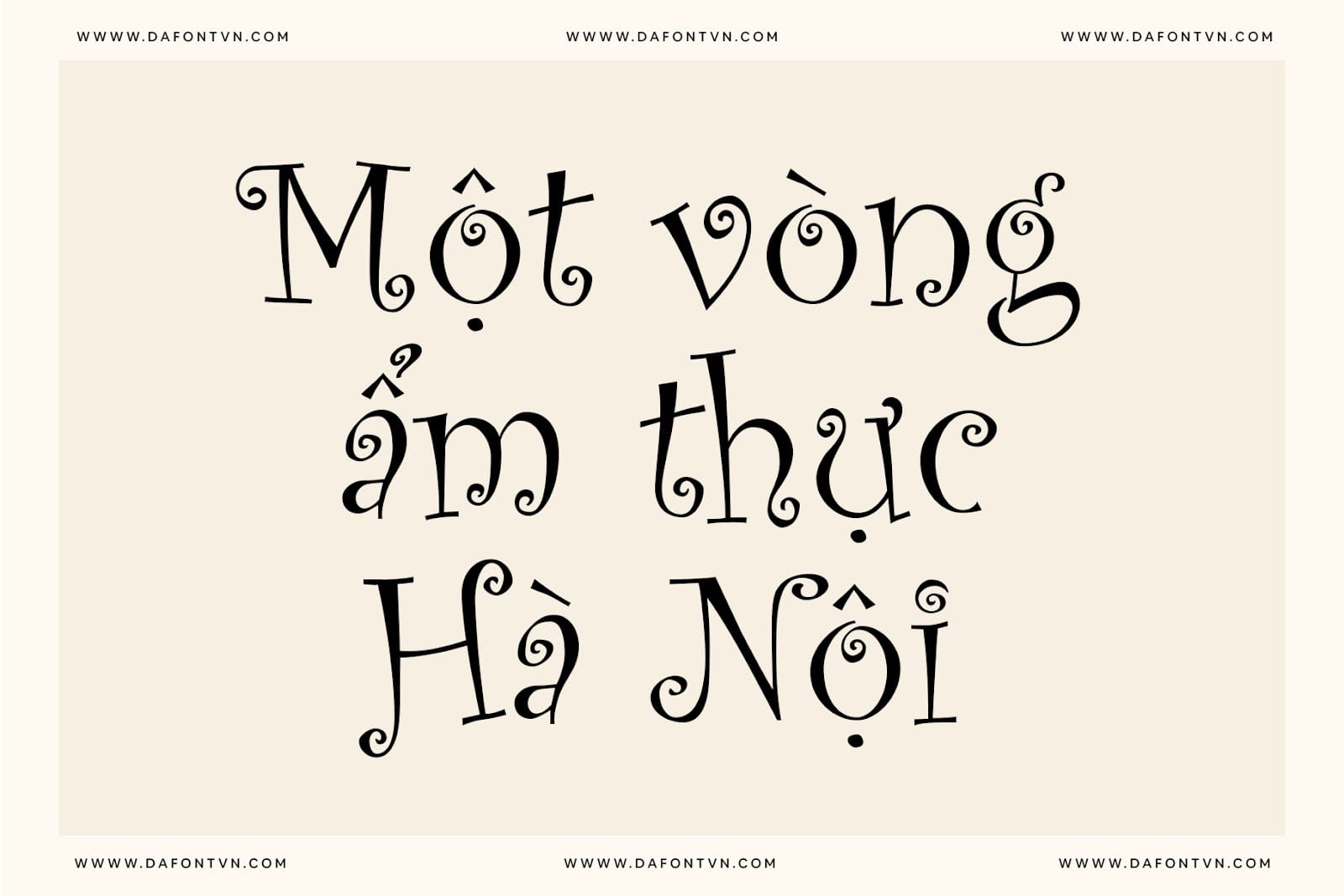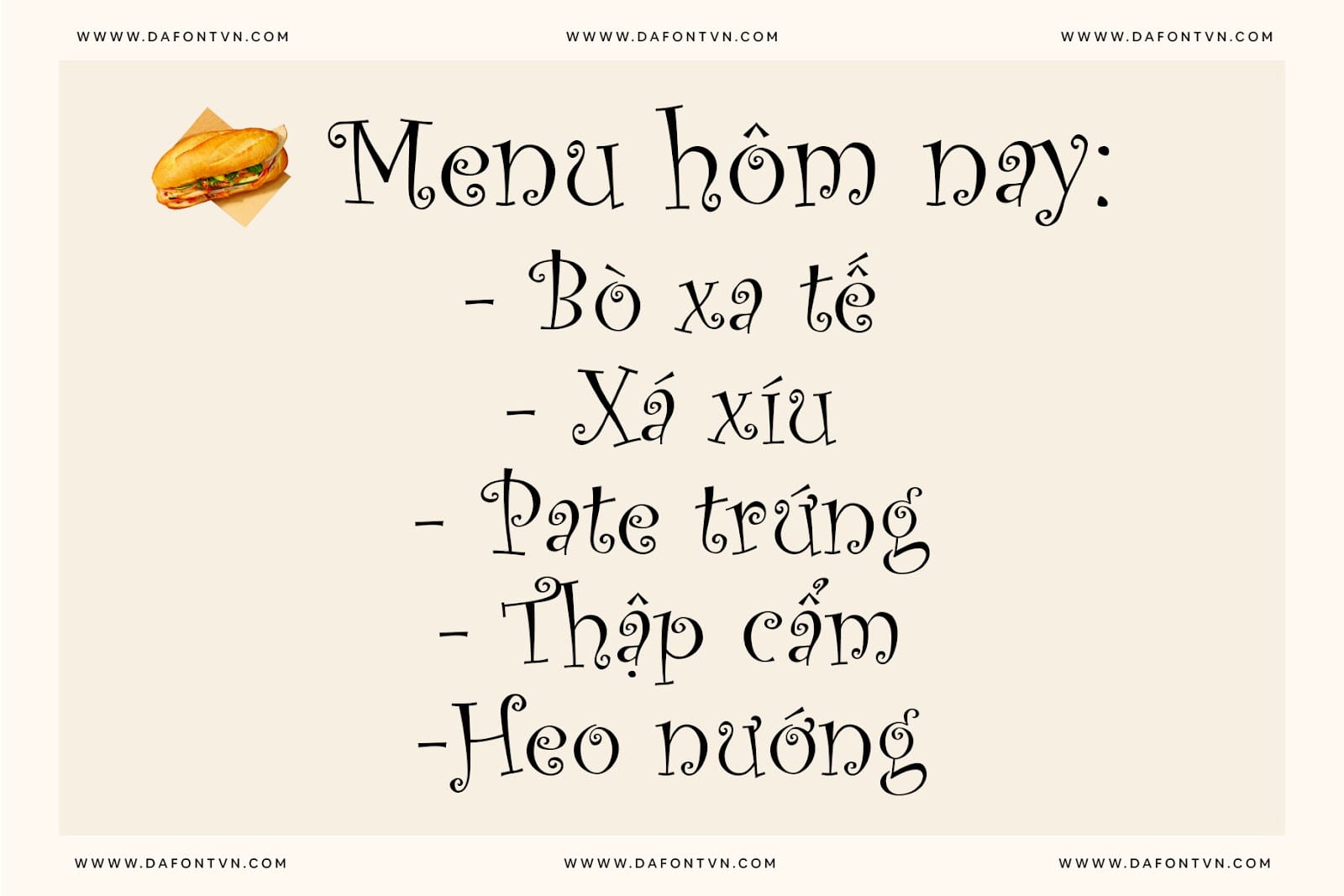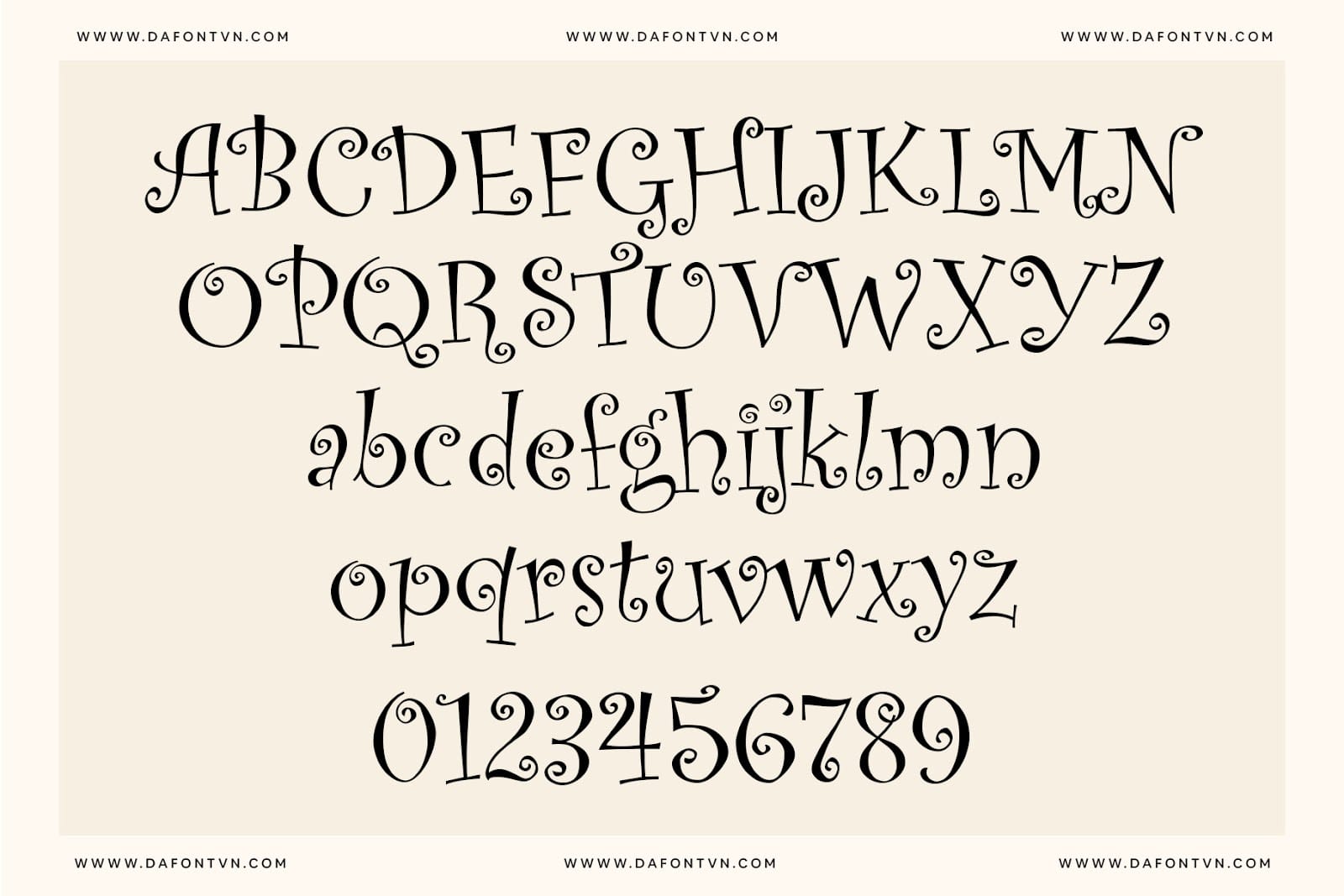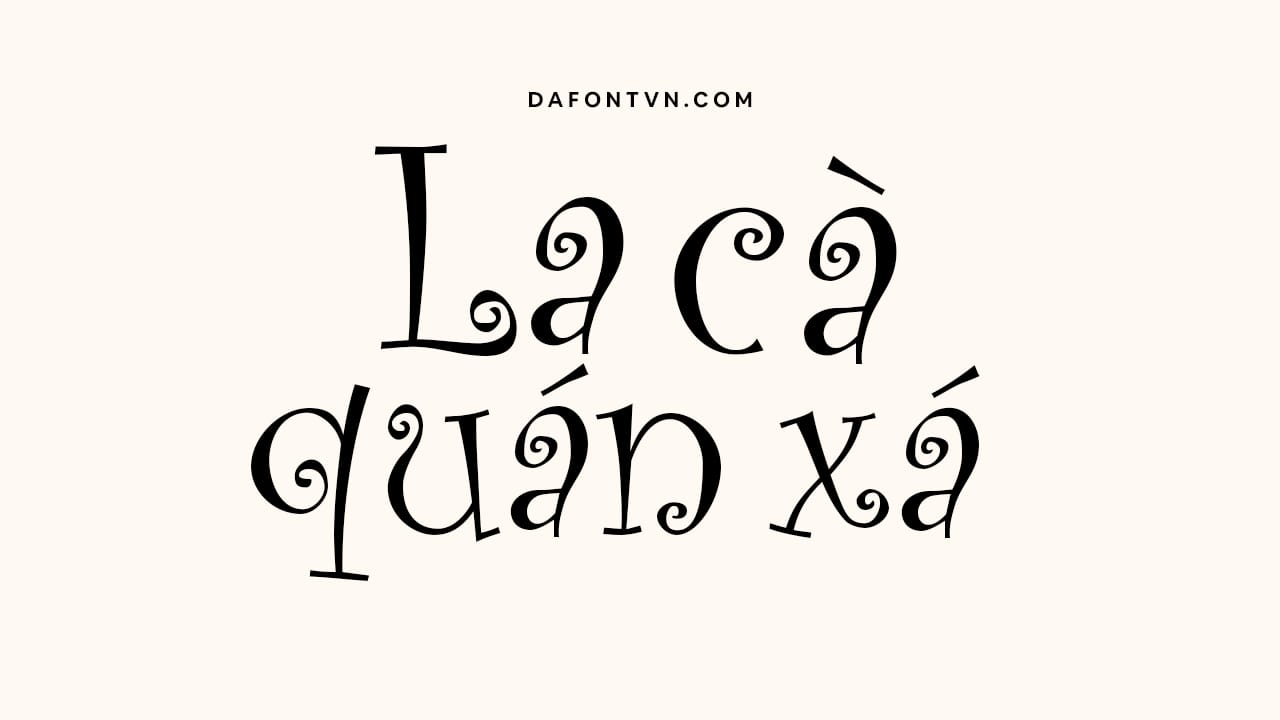
Curlz là một kiểu chữ hiển thị với các nét uốn lượn. Nó khác biệt với các kiểu chữ khác, được đặc trăng bởi các nét lượn sóng và xoáy ở đầu hoặc cuối các chữ cái. Curlz được thiết kế như một kiểu chữ trang trí giản dị.Phông chữ Curlz việt hóa được sử dụng tốt nhất cho tiêu đề. Curlz thích hợp cho thiết kế như thực đơn, biển hiệu, thiệp chúc mừng, menu…